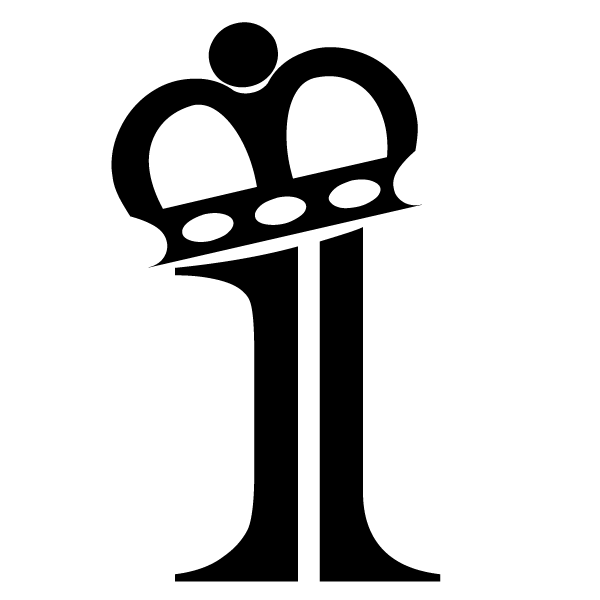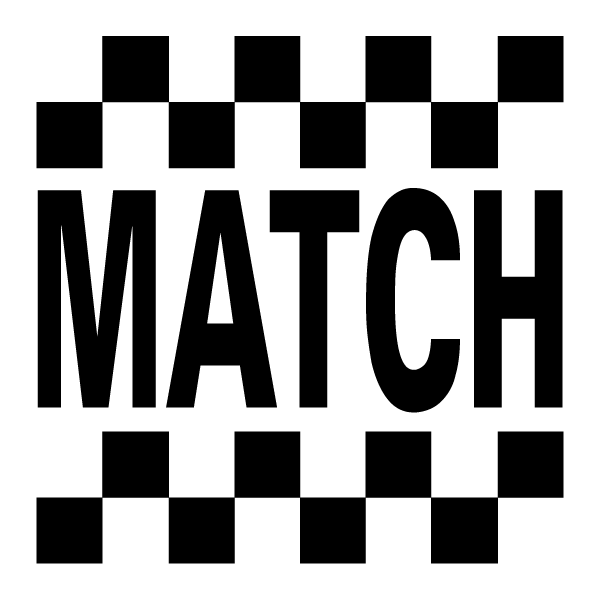
La Fuente Chess Miscel ofrece una colección variada de imágenes y figuras relacionadas con el ajedrez, perfectas para usar como viñetas o clip art en publicaciones, materiales didácticos, o proyectos gráficos. Sus elementos incluyen piezas tradicionales, símbolos y otros elementos decorativos que enriquecen visualmente cualquier contenido.